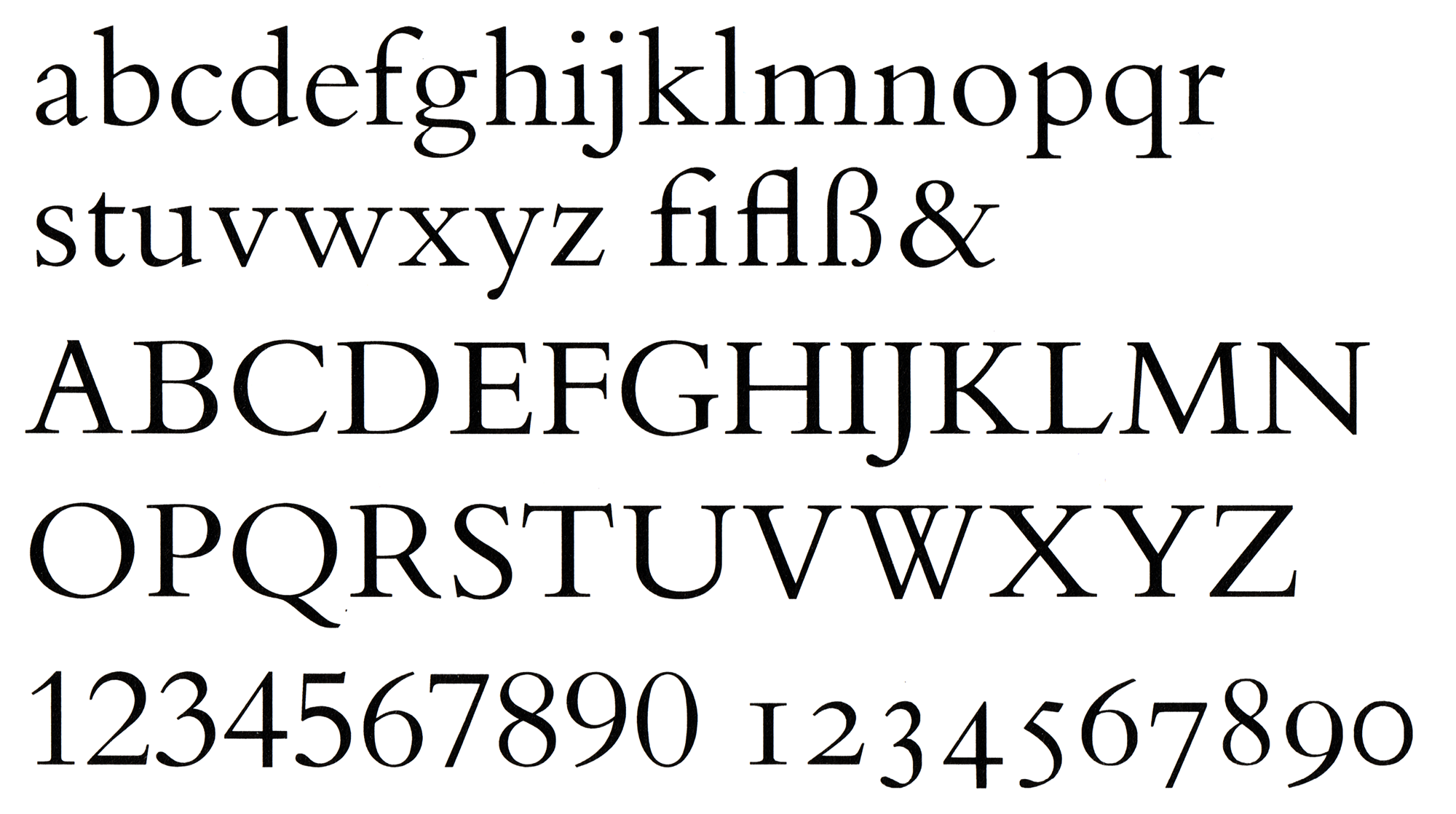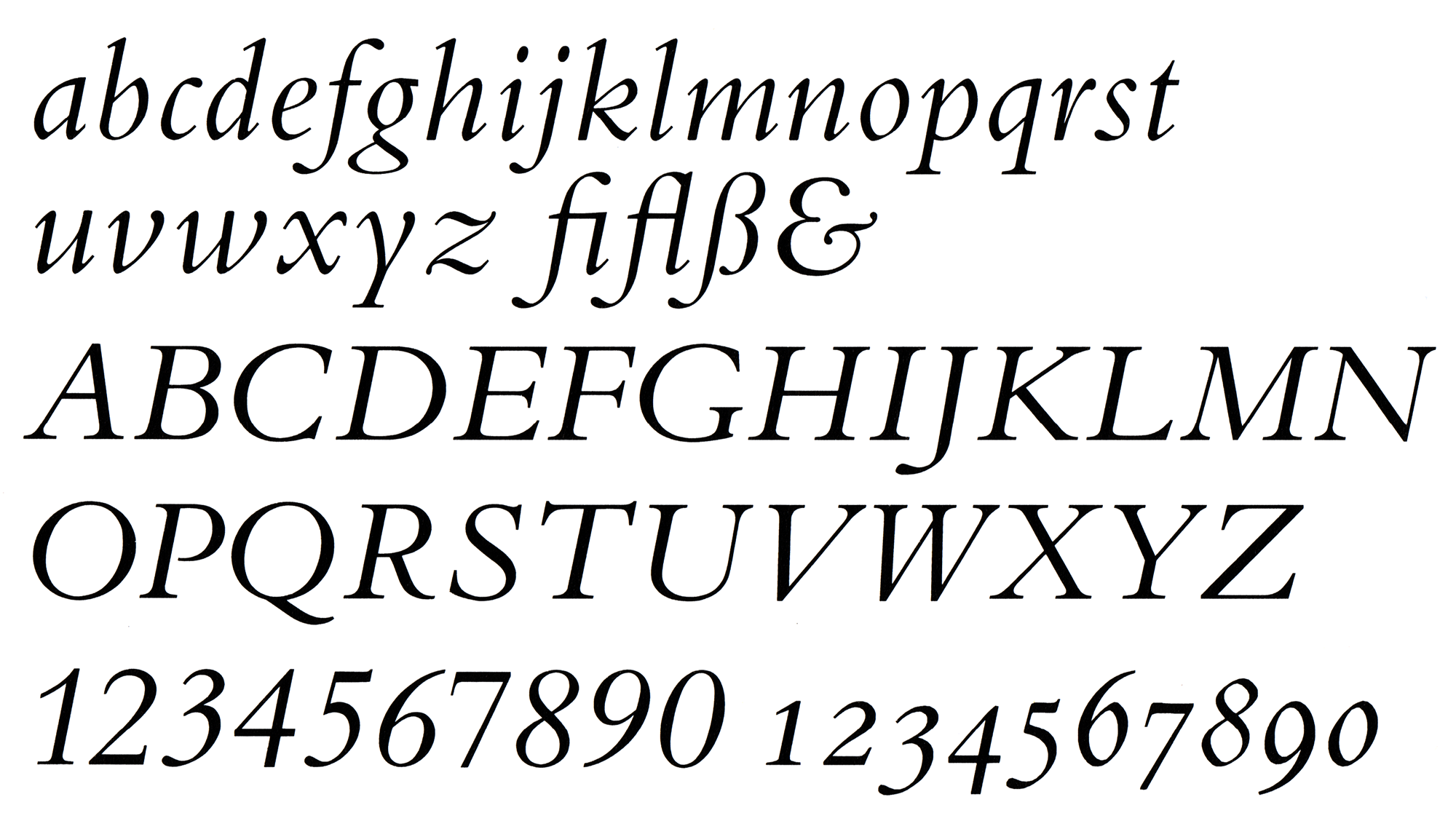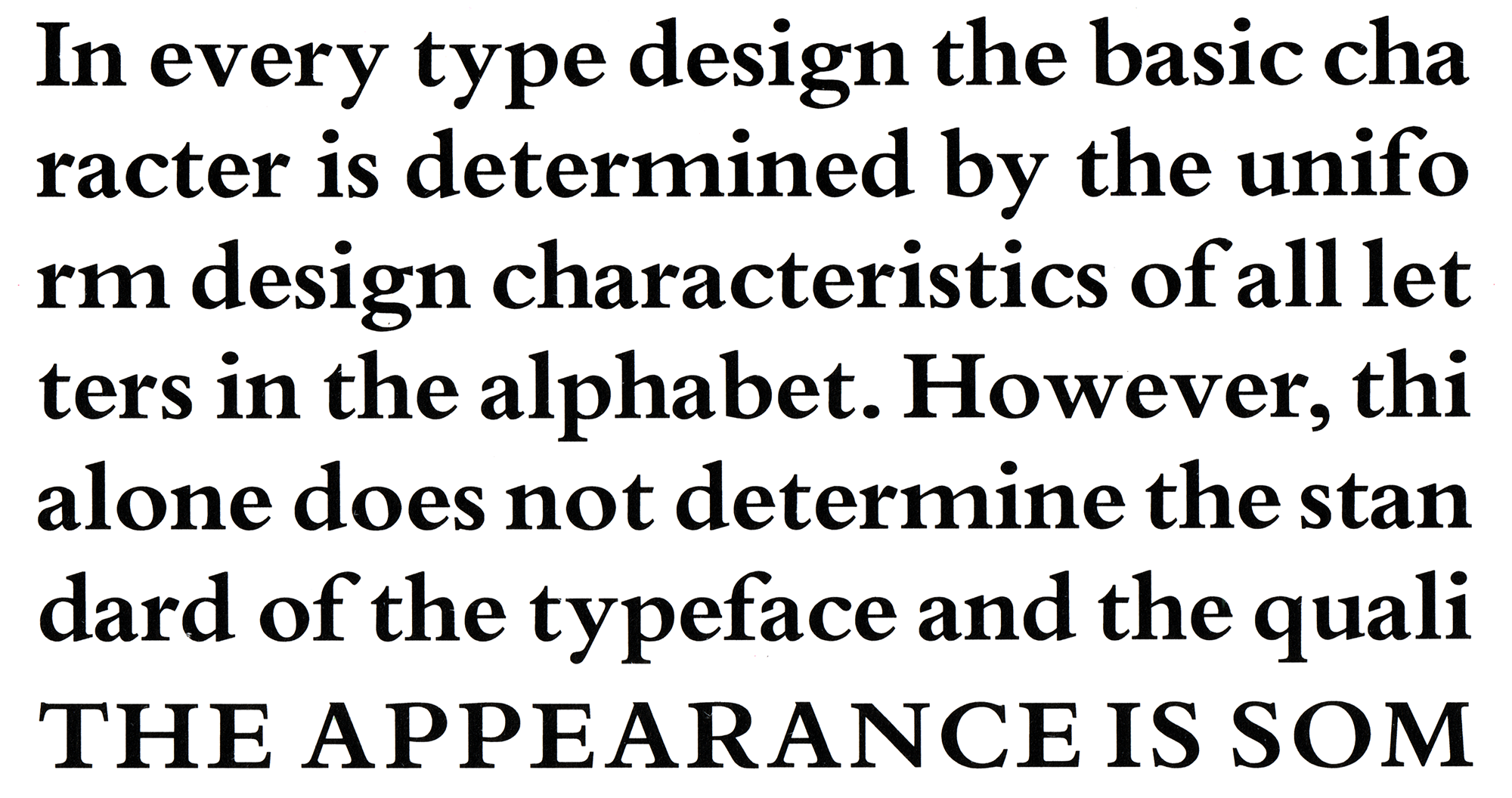
- 1929
- Antiqua humanistisch
Die Bembo wurde vom venezianischen Stempelschneider Francesco Griffo geschnitten und erstmals für den Druck des Buches »Petri Bembi de Aetna Angelum Chalabrilem liber« (1495–1496) in der Druckerei von Aldus Manutius benutzt. Der Nachname von Pietro Bembo, dem Autor dieses Werkes, wurde später zur Bezeichnung dieser Schrifttype benutzt.
Im 20. Jahrhundert fand die Schrift wieder weite Verbreitung, denn Monotype brachte unter der Leitung von Stanley Morrison ab 1929 eine umfangreiche Bembo-Familie heraus. Für den dabei hinzugefügten kursiven Schnitt diente ein Musterbuch des italienischen Schreibkünstlers Giovanni Tagliente von 1524 als Inspiration.